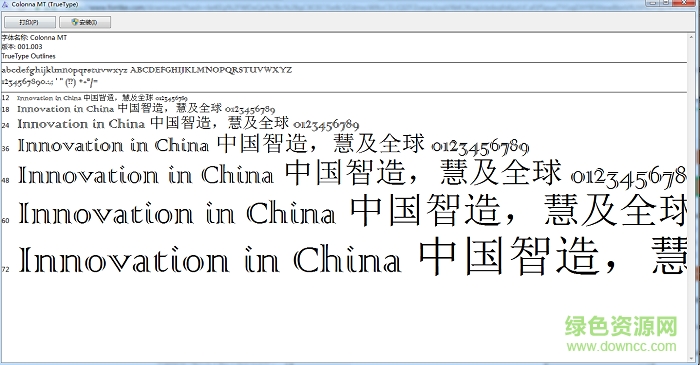
colonna mt字體是一款華麗大氣的英文雙線字體,每一個字母都是由雙線構(gòu)成,個性鮮明,十分吸睛,可以用在廣告、雜志等方面,需要的朋友快來綠色資源網(wǎng)下載吧!
襯線字體指的是字形筆畫在首位的裝飾和筆畫的粗細(xì)不同,所以「襯線」又被稱為「字腳」。
無襯線字體則沒有筆畫首尾的裝飾,所有筆畫的粗細(xì)也相同。無襯線體在 80 年代開始興起,在當(dāng)時被稱為 Grotesque(荒唐的)或 Gothic(哥特的),因為天然的技術(shù)感和理性氣質(zhì),無襯線字體多為科技型企業(yè)所青睞。